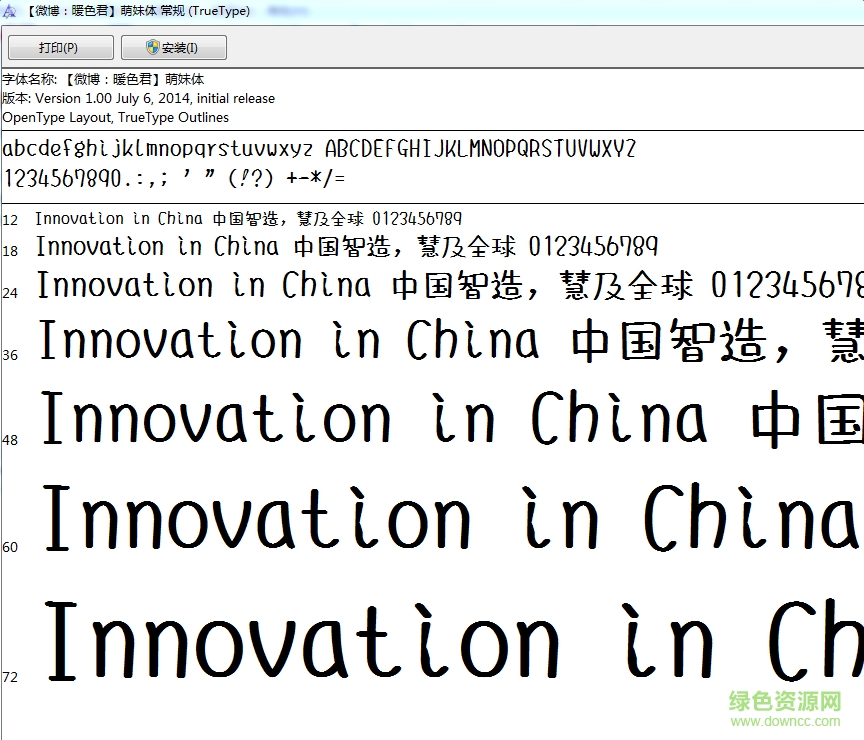
暖色君萌妹體字體
暖色君萌妹體字體是一款清新文雅風(fēng)格字體軟件,萌妹體筆畫圓潤,無堅(jiān)硬棱角,看似漫不經(jīng)心,卻盡顯萌萌噠氣質(zhì),整體效果十分可愛迷人,感興趣的朋友歡迎到綠色資源網(wǎng)下載體驗(yàn)!
暖色君萌妹體是一款應(yīng)用于藝術(shù)設(shè)計(jì)方面的簡體中文字體,該字體筆畫粗壯,尾部的甩尾有力且有豐富的筆觸細(xì)節(jié),大字效果突出且引人注目;并且最大程度還原作者書寫字形,細(xì)節(jié)表現(xiàn)完整,且字庫完整,可以廣泛應(yīng)用于名片設(shè)計(jì)、新聞媒體、宣傳海報(bào)、ppt、影視制作以及內(nèi)容用字等領(lǐng)域。